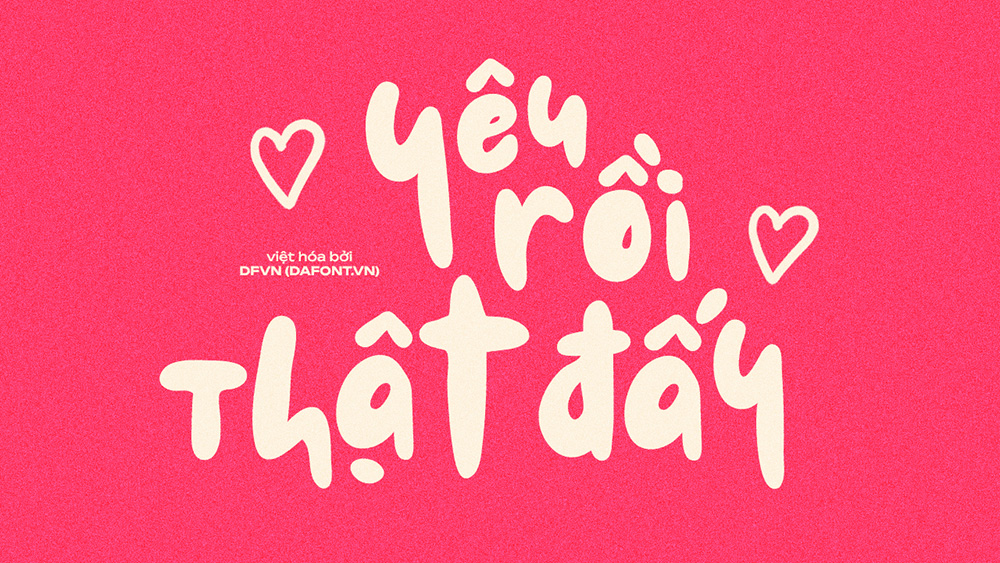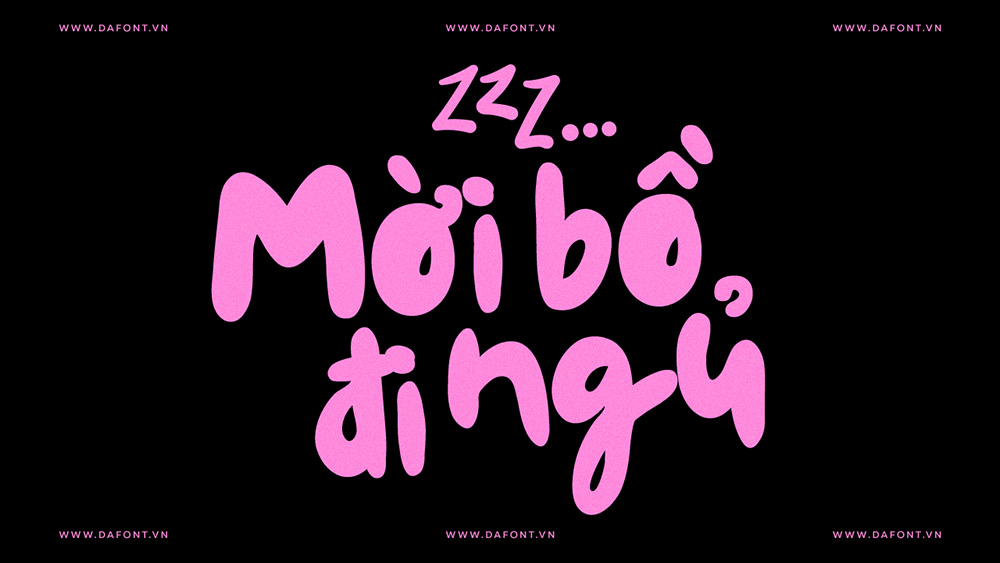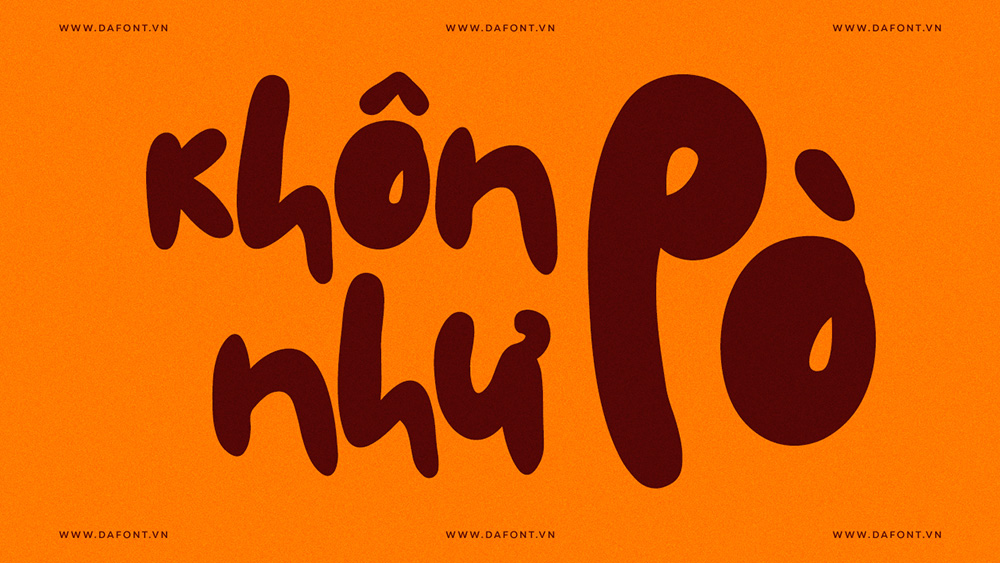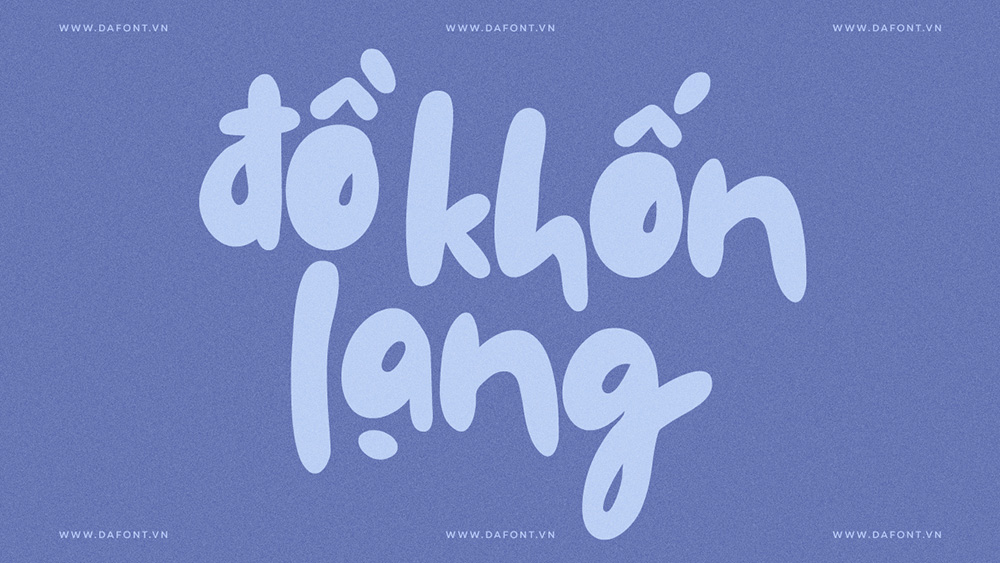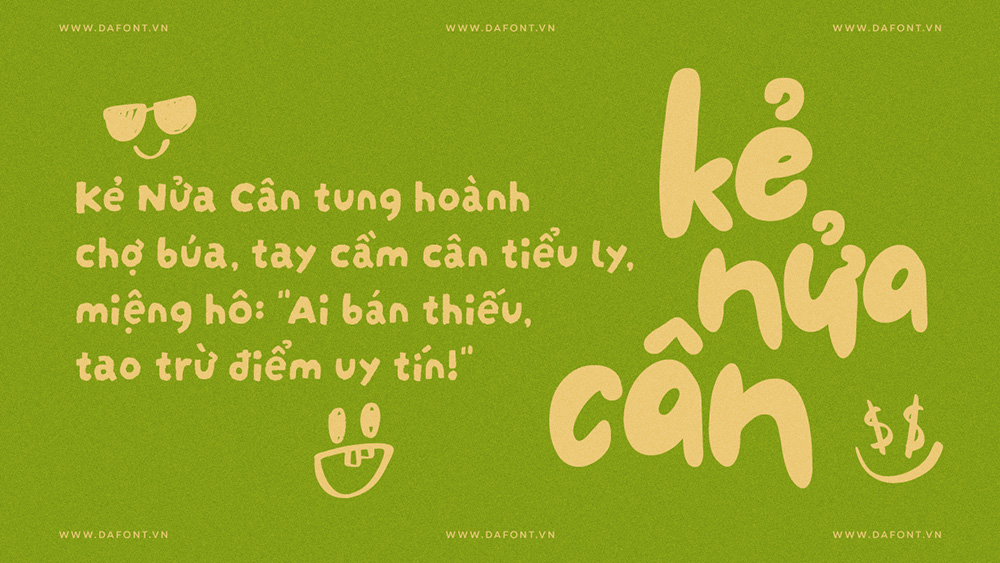
Font Việt Hóa - Le Petit Cochon Mang Phong Cách Đáng Yêu, Vui Nhộn
Le Petit Cochon là một font chữ script (chữ viết tay) có phong cách đáng yêu, mũm mĩm (chubby) và hiện đại, được thiết kế để làm nổi bật mọi ý tưởng thiết kế với nét độc đáo riêng biệt. Font này rất phù hợp cho các dự án cần sự vui nhộn, dễ thương như poster, thiệp mời, bìa sách thiếu nhi, bao bì sản phẩm hoặc các thiết kế sáng tạo mang tính cá nhân.
Đặc điểm nổi bật DFVN Le Petit Cochon
- Phong cách: Đây là một font chữ script (chữ viết tay) có phong cách rất dễ thương, mũm mĩm (chubby) và hiện đại, với nét chữ bo tròn, mềm mại, tạo cảm giác thân thiện và vui nhộn.
- Tính thẩm mỹ: Mỗi ký tự được thiết kế chăm chút, giữ cân bằng hài hòa giữa sự ngộ nghĩnh và tính chuyên nghiệp, giúp font vừa trang trí tốt vừa dễ đọc.
- Ứng dụng đa dạng: Rất phù hợp cho nhiều dự án sáng tạo như poster, thiệp mời, logo, bìa sách thiếu nhi, bao bì sản phẩm, bài đăng mạng xã hội, đặc biệt là các thiết kế cần phong cách trẻ trung, cá tính.
- Việt hóa đầy đủ và tối ưu: DFVN Le Petit Cochon được chỉnh sửa lại 1 số dấu và ký tự, kerning cũng như tối ưu để sử dụng trên bất kỳ nền tảng nào.
- Đặc trưng cá nhân: Font mang nét “vibey” – đầy cảm xúc và sức sống, phù hợp cho các nội dung truyền thông xã hội và các thương hiệu muốn tạo ấn tượng khác biệt và đáng yêu.
DFVN Le Petit Cochon là sự kết hợp hài hòa giữa sự dễ thương, sáng tạo và tính chuyên nghiệp, giúp các ý tưởng thiết kế trở nên nổi bật và gần gũi hơn.